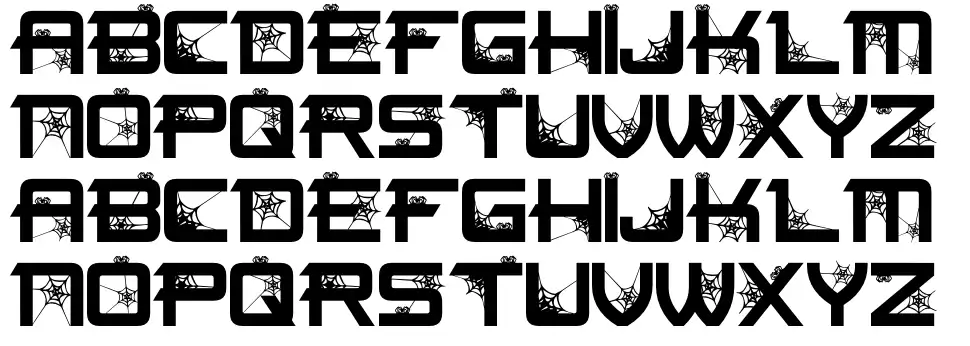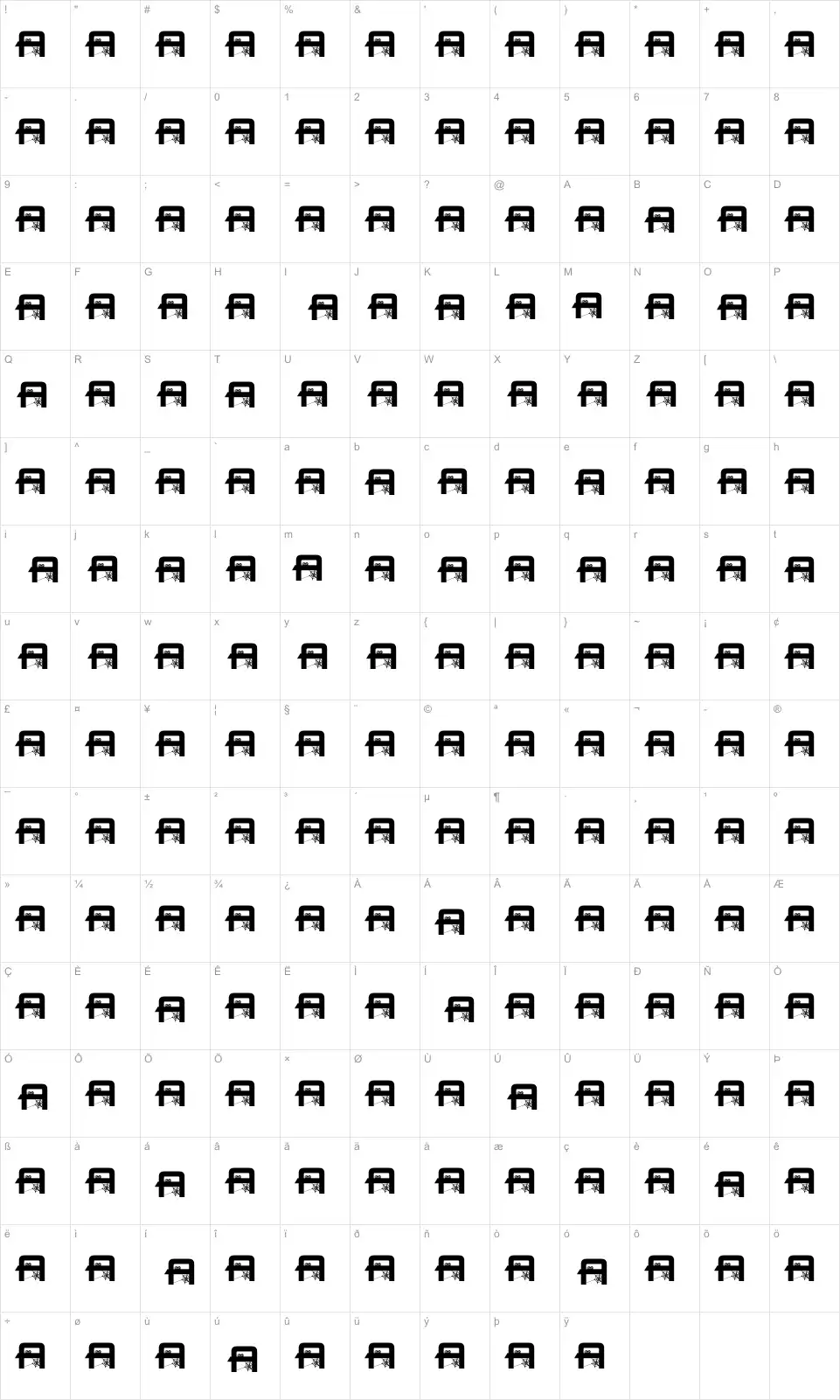
Spider Font – Download Grátis
A fonte Spider Font, criada por Javierq, é perfeita para aqueles que estão buscando uma fonte inovadora para seus projetos de desfile de moda, materiais de decoração ou em qualquer outro tipo de trabalho de arte gráfico que requer uma fonte desafiadora e original. Adicionada em 12 de julho de 2022, esta font Holiday/Halloween é licenciada sob uma licença gratuita, garantindo que seja acessível para todos os profissionais de design. Com formato TTF, é simplesmente uma opção de fonte única que pode ser facilmente integrada em qualquer projeto. Com um tamanho de 16 KB, a Spider Font é levemente pesada e ideal para criar efeitos impressionantes em seus trabalhos. Se você estiver procurando por algo diferente e desafiador, a fonte Spider Font é uma ótima escolha para sua próxima criação. Com mais de 6543 downloads, já é um sucesso no mercado de fontes digitais.